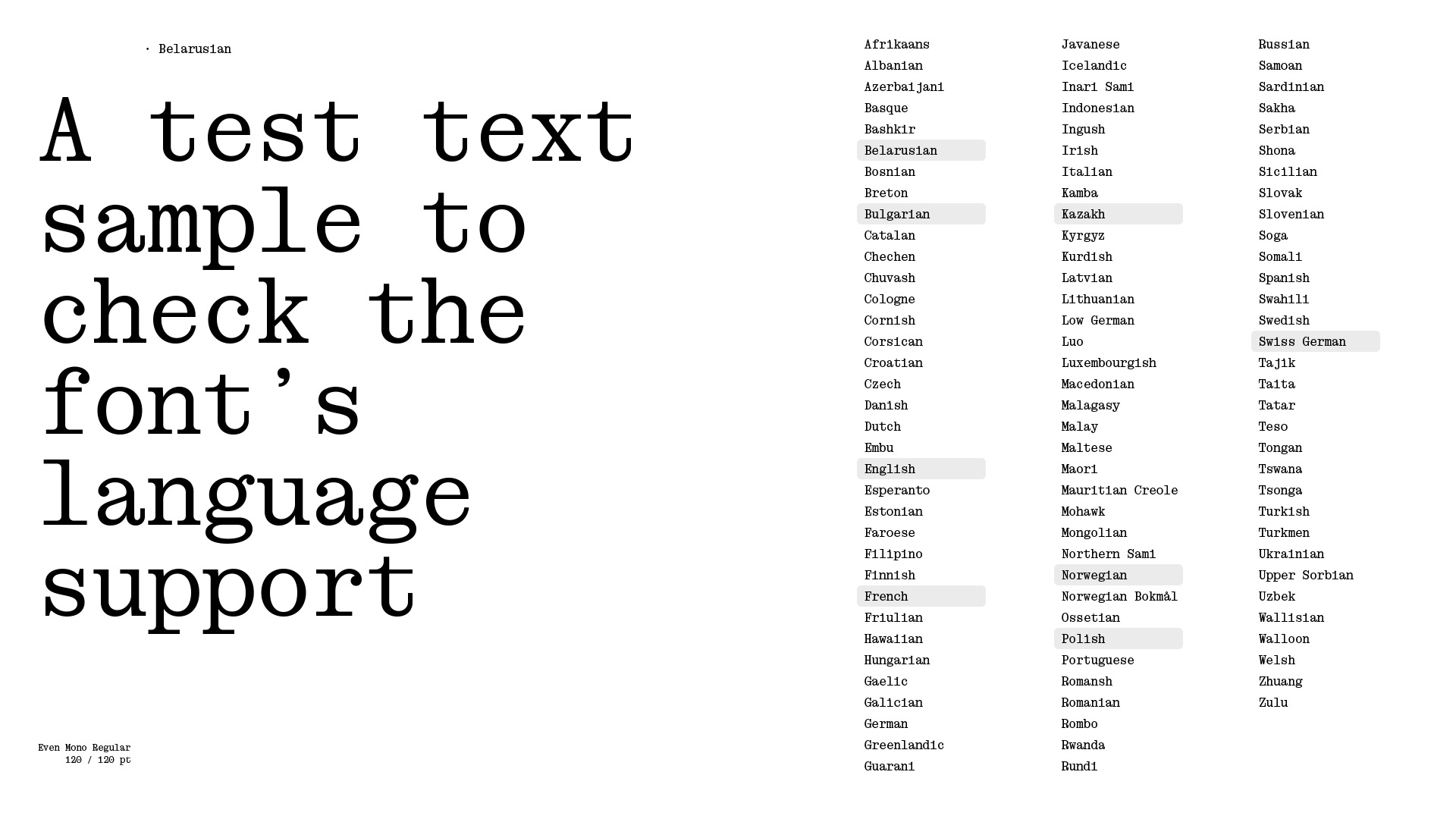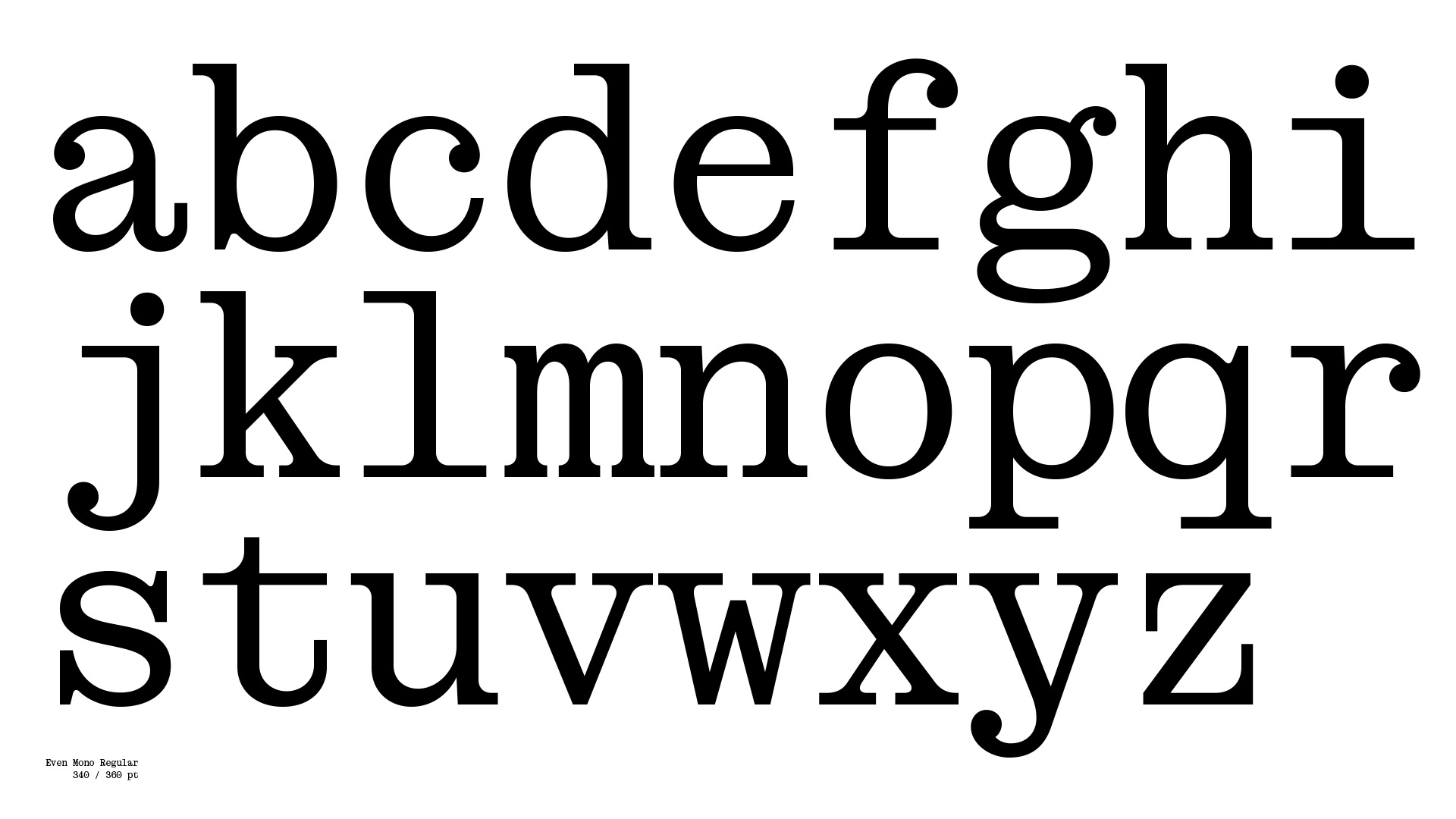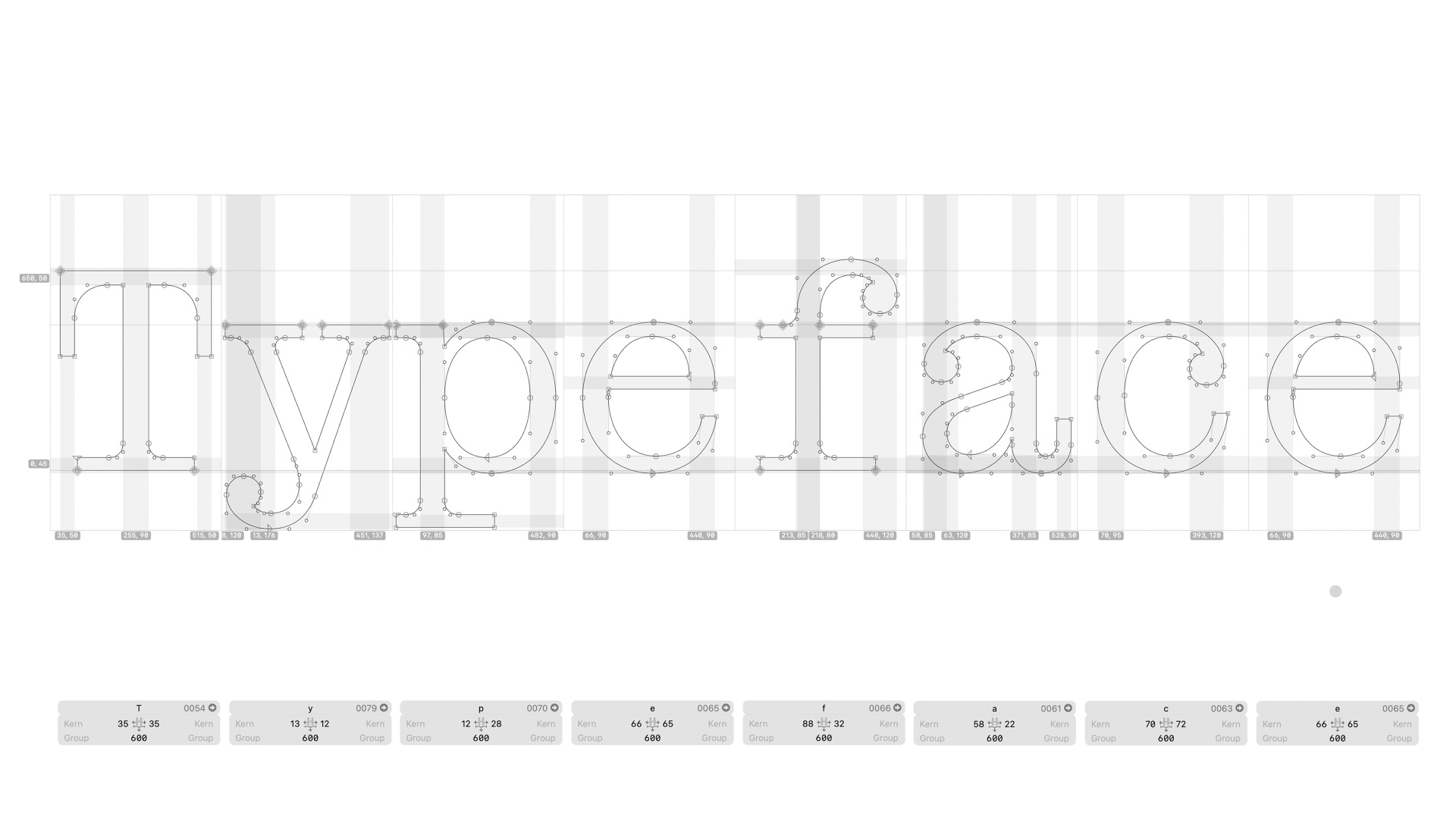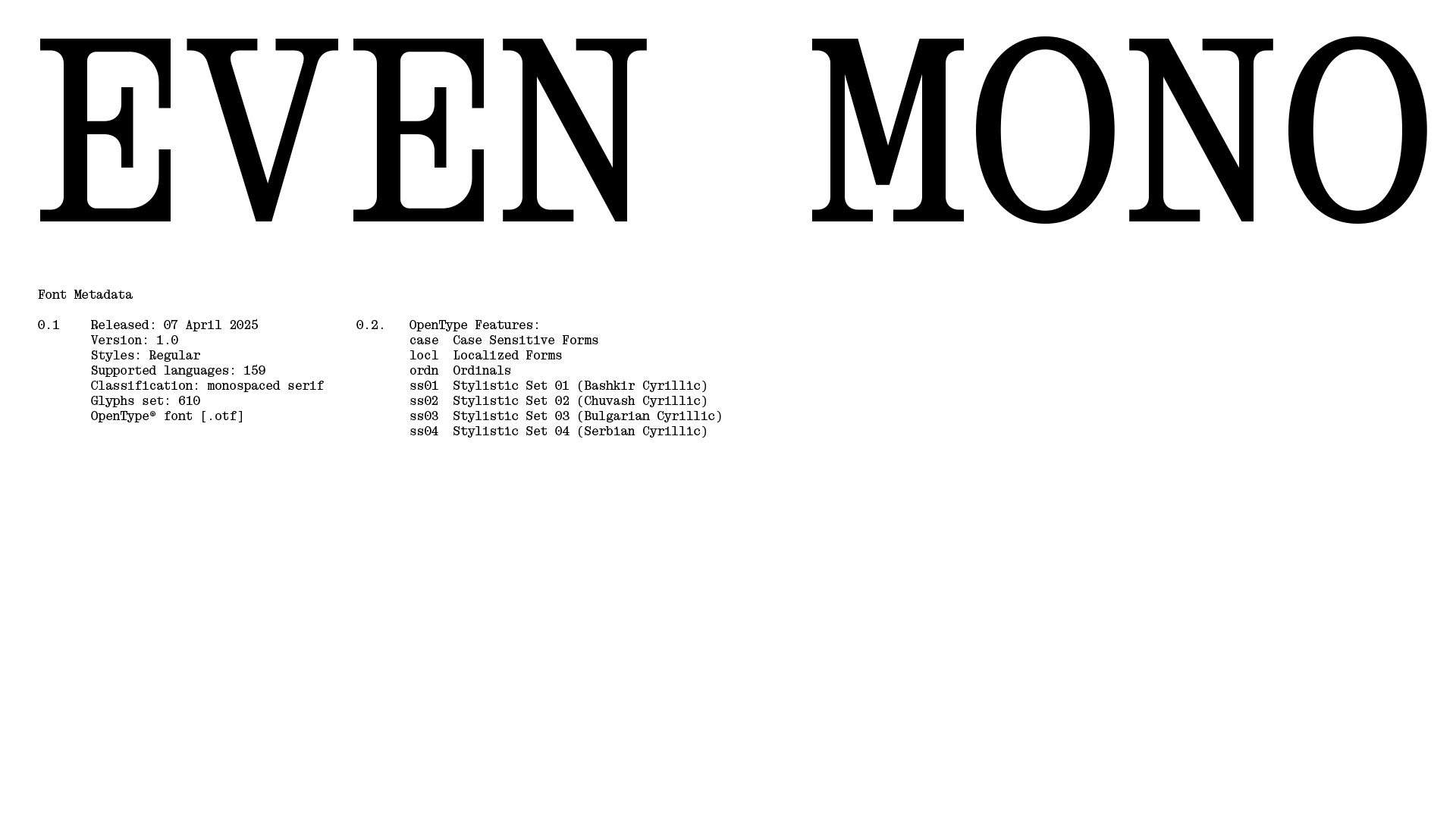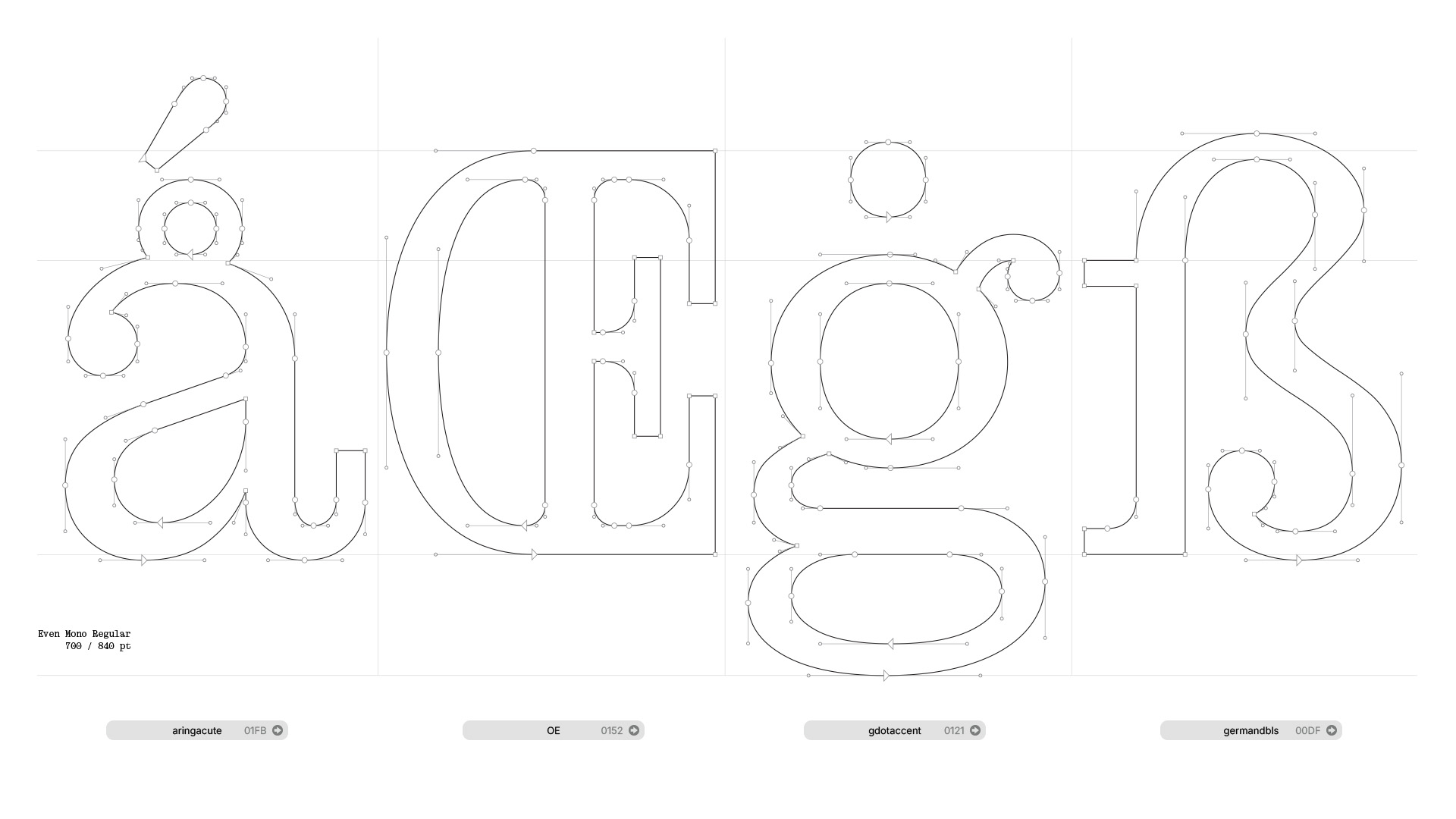
Тиражный шрифт
Even Mono
Even Mono сочетает строгий моноширинный ритм машинописи с элегантностью классической шотландской антиквы. Плотные пропорции и чёткие детали обеспечивают удобочитаемость даже в мелких размерах, сохраняя визуальную выразительность. Шрифт балансирует между технической нейтральностью и тёплой человечностью, предлагая свежий взгляд на моноширинную эстетику.